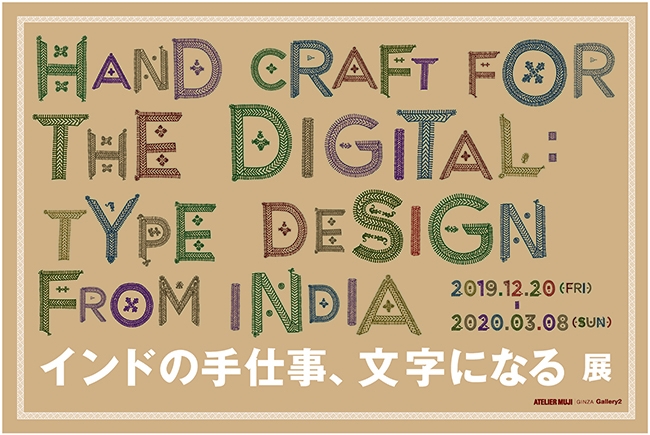
「インドの手仕事、文字になる」展
ATELIER MUJI GINZAは、2019年12月20日(金)から2020年3月8日(日)まで、ATELIER MUJI GINZA Gallery2にて「インドの手仕事、文字になる」展を開催することを発表した。
「インドの手仕事、文字になる」展では、地域固有の文化とイノベーションが融合し、社会に新しい価値を生み出すインドのデザインにおいての文字をめぐる挑戦を紹介する。
インドでは、インドのグラフィック・デザイナーであるイシャン・コースラ氏により「タイプクラフト構想」というプロジェクトが2011年に立ち上げられた。「タイプクラフト構想」は、デザイナーとインド各地の工芸や民俗芸術の職人がワークショップ形式で、独自の英文書体を共同制作し、地域の生活に根ざした入れ墨、刺繍、陶芸、絵画など幅広い分野の職人たちと時間をかけてその特性や個性に合わせたワークショップを実施し、最終的にはインド全29州、それぞれ異なる書体の完成を目指している。
また、それらの書体をデジタルフォントとして製品化することは、デザインの可能性や職人である女性たちの新たな職域を広げる取り組みでもあり、これは近代化の波に消えゆくインドの手仕事を未来につなげる活動にも繋がっている。
タイプクラフト構想
2011年にインドのグラフィック・デザイナーであるイシャン・コースラ氏が立ち上げたプロジェクト。ワークショップ形式で、デザイナーとインド各地の生活工芸や民俗芸術にたずさわる職人が、独自の英字書体を協同制作。現地に赴き時間をかけながら多様な分野の職人と5個の書体を制作した。最終的にはインド全29州それぞれ異なる活字書体29種の完成を目指しており、それらの書体をデジタル化して商品に発展させる活動により、職人たちの新しい職域を広げようとしている。